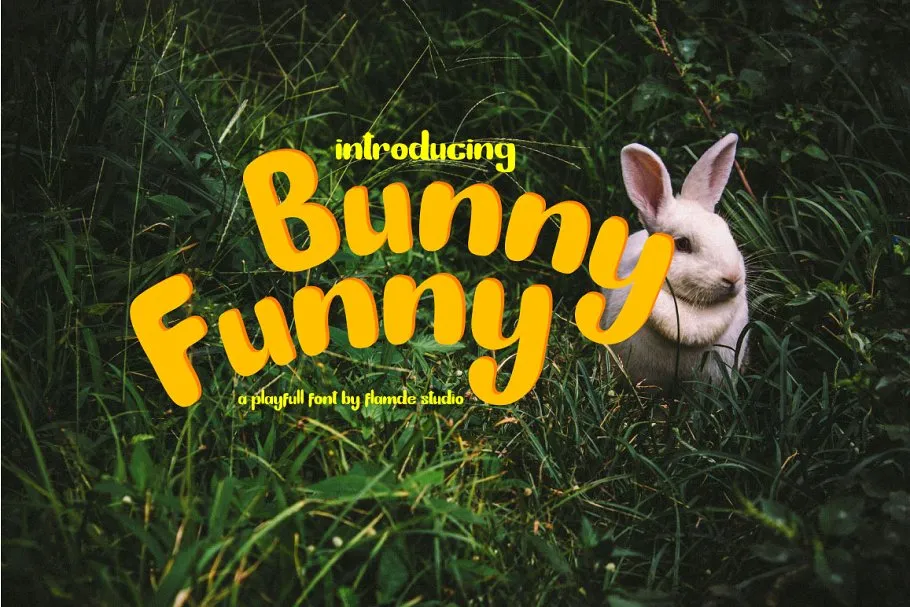
Introduzimos Bunny Funny, uma nova font criada pela Flamde Studio. Esta é uma fonte com letras em minúsculas e maiúsculas que transmite a sensação de rapidez ao esboçar algo rapidamente. O Bunny Funny é uma fonte desenhada à mão real, dando um toque pessoal aos seus projetos. Perfeita para diversas utilizações como design editorial, marca, citação artística, títulos de livros e capas, postagem, design de roupas, embalagens de produtos, etiquetas, eventos especiais ou qualquer coisa que precise daquela sensação única desenhada à mão. Este Bunny Funny Playful Font é uma escolha perfeita para aqueles que buscam um toque autêntico e único em seus trabalhos gráficos.